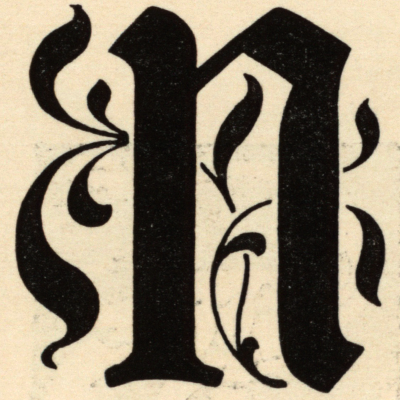
- 1908
- Antiqua dekorativ
Die Bombe ist eine schmalfette Werbeschrift des Münchner Grafikers Otto Ludwig Naegele. Sie erschien 1908 bei Ludwig & Mayer. Drei Jahre später erschien vom gleichen Gestalter als Feder-Antiqua ein gestalterisch verwandter Schnitt, der jedoch deutlich breiter und mit geringerer Strichstärke ausgeführt wurde.
Eine kostenlose Digitalisierung gibt es von Peter Wiegel. Eine professionelle, umfangreich ausgebaute Version gibt es von FDI Type.